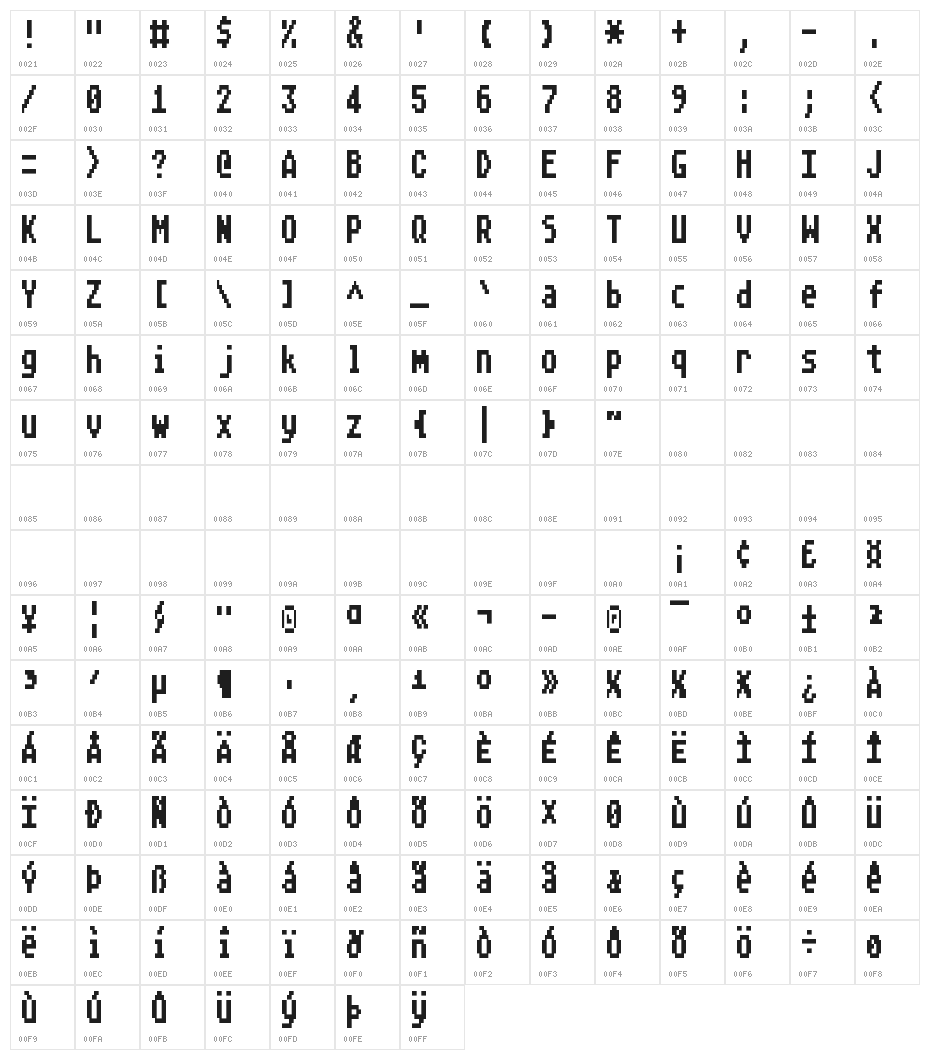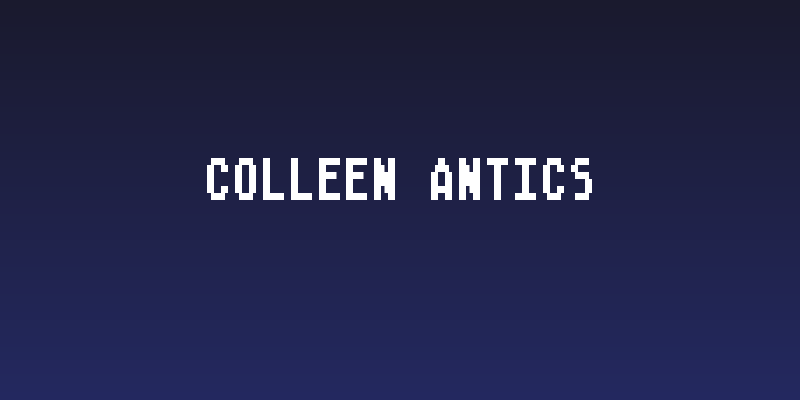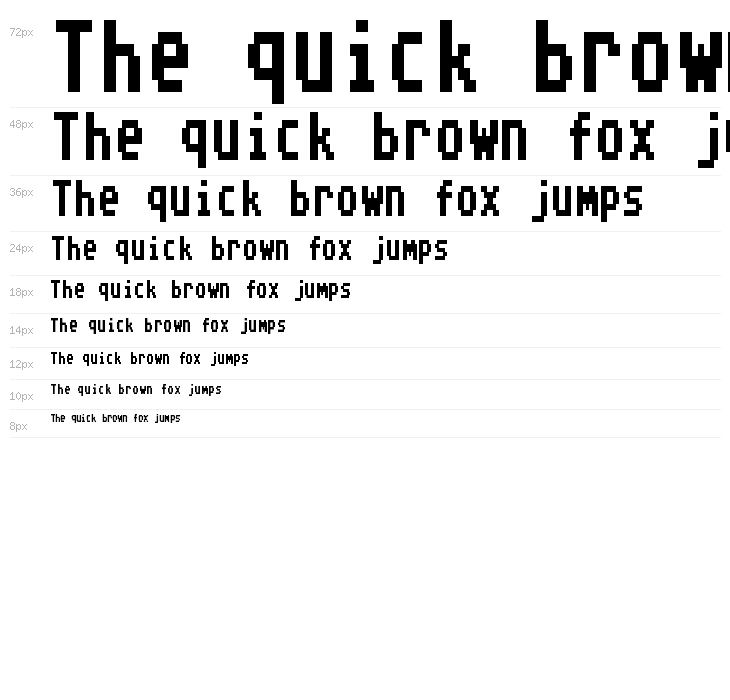
Colleen Antics Font
✎ Pixel
| Stile generale | Retro, Digital |
| Caso d'uso | Headlines, Logos, Digital Art |
| Progetti proposti | Ideal for retro-themed designs, video game graphics, digital art projects, and any creative work that seeks to evoke nostalgia for early computing and gaming eras. |